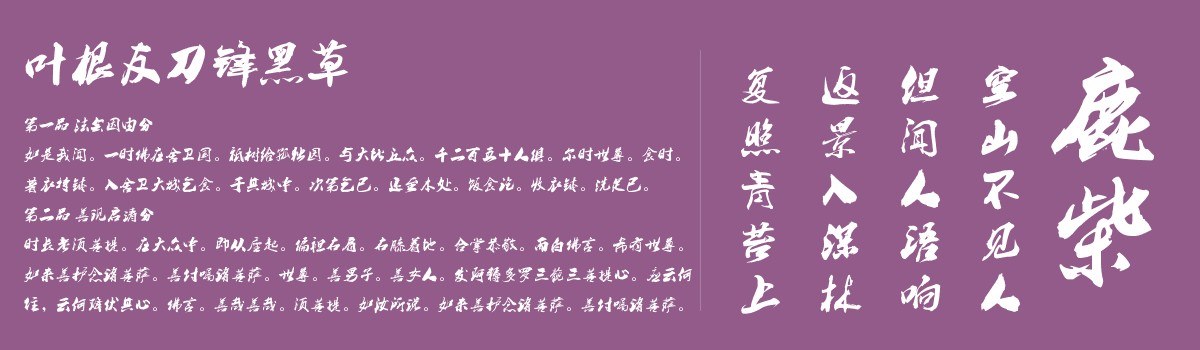
叶根友刀锋黑草
创作年代:2010年
字体字数:6763个中文汉字以及其他英文字母和阿拉伯数字
字体介绍
叶根友刀锋黑草这是一款叶根友字体系列最受欢迎的字体之一。叶根友刀锋黑草笔画风格犹如刀锋剑影,笔起笔落间一股侠客风的力量萦绕在字里行间,赋予了中国汉字的一种新的犀利,行书与叶氏创新书法的结合,无不演绎出不同的汉字角度。叶根友刀锋黑草广泛应用于社会各界的广告招牌、影视作品以及游戏应用等。叶根友刀锋黑草也是一款刀锋犀利的笔画结构,在字体风格上,追求了一种鲜明向上的特点,使整个字型灵动而不失严谨,飘逸俊秀,保留了书法原作的原始元素。